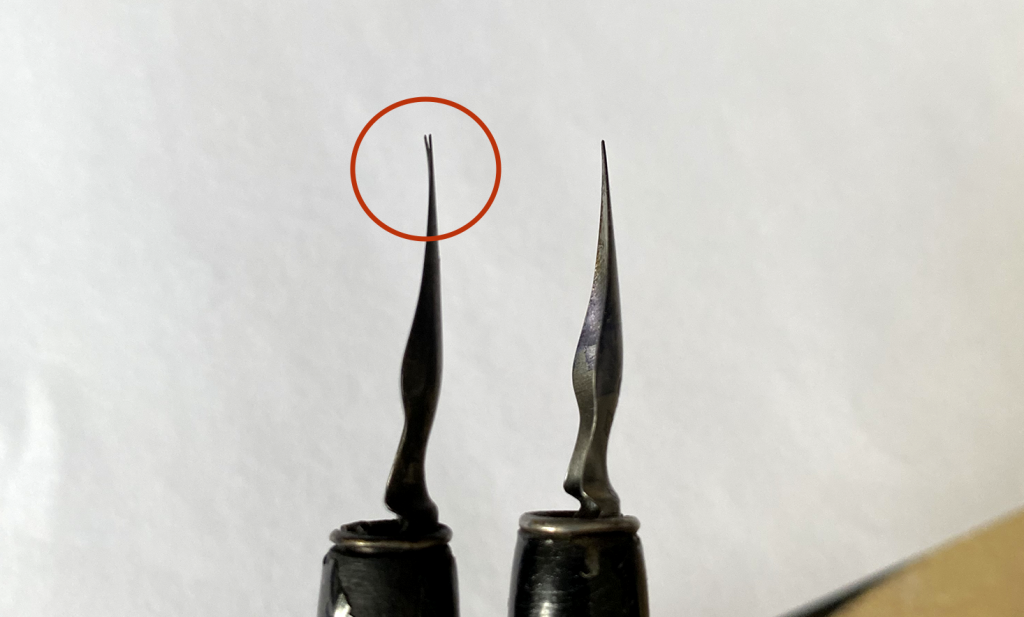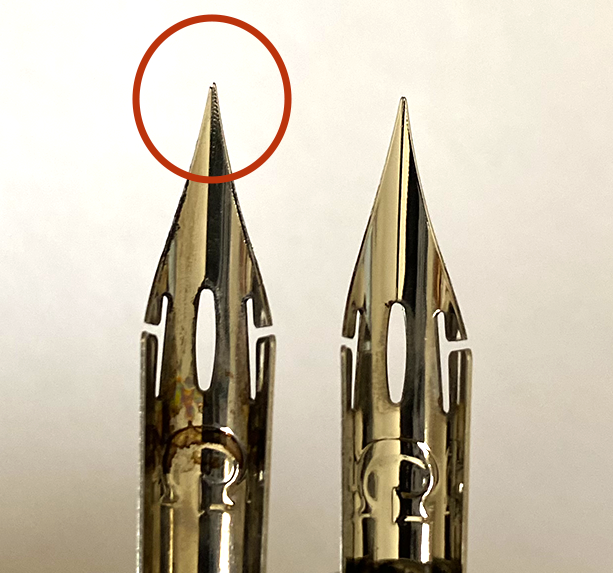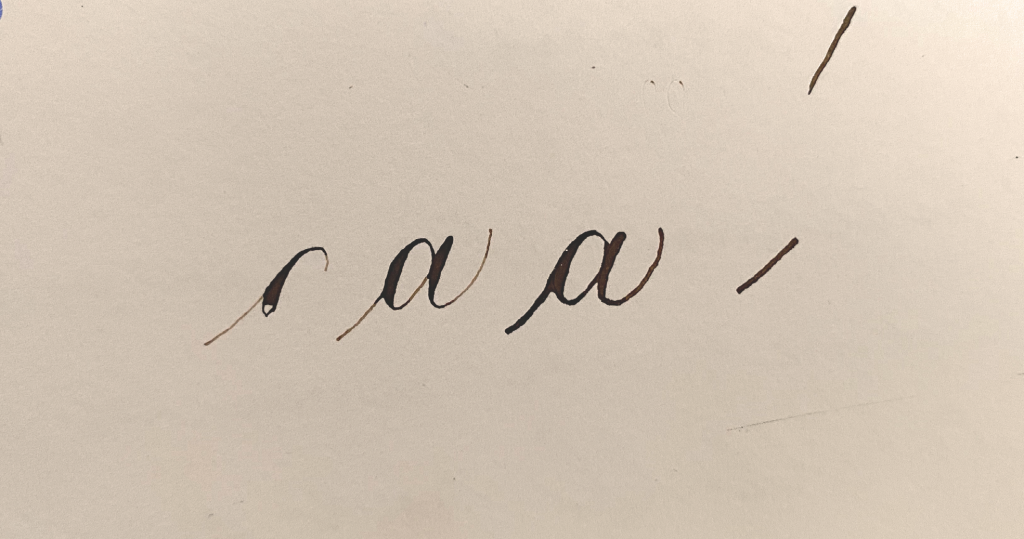
Cet été j’ai repris doucement la calligraphie à la plume pointue et j’ai peiné puissance 10. Mes traits étaient vraiment horribles et la plume accrochait considérablement le papier. Pensant que j’étais rouillée après de longs mois d’arrêt, j’ai persisté, en vain. J’ai incriminé le papier, puis l’encre. J’ai nettoyé 3 fois la plume, tourné ma feuille dans tous les sens, modifié l’inclinaison du porte-plume… Au passage je me suis un peu énervée aussi… Bref ! Jusqu’au moment où je me suis dit : « Essayons avec une plume neuve ! ». Et là, bien sûr, miracle !
Les plumes s’usent et certaines sont même très fragiles. Surtout si comme moi vous avez la main un peu lourde. Même avec une plume robuste comme la Nikko G, au fil des utilisations, ça se gâte.
Comment reconnaître qu’une plume est définitivement usée ?
Les signes d’usure sont différents pour les plumes pointues et les plumes biseautées. D’ailleurs, ces dernières s’usent nettement moins vite. La plume pointue est ultra fine, donc plus fragile, logiquement. Il m’est même arrivé d’en casser (et oui, en faisant de la gestuelle !).
Plume pointue usée : les signes
• La plume accroche le papier, alors que ce n’est pas le cas habituellement.
• Les déliés (parties fines de la lettre), sont plus gras que d’habitude.
• L’encre s’écoule mal : elle ne s’écoule pas sur les ascendantes et/ou fait des pâtés sur les descendantes.
La finesse du trait avec une plume usée, à droite
Que faire ? Généralement, tout ceci vient du fait que les 2 lames ne sont plus alignées et/ou que la pointe de la plume s’est légèrement courbée au fil des utilisations.
Exemple de lames abîmées qui ne sont plus alignées
Très difficile à voir à l’oeil nu, la pointe de gauche est très légèrement cassée
Il n’y a rien à faire, malheureusement, il faut passer sur une plume neuve.
Plume biseautée usée : les signes
• La plume manque de précision dans les traits d’attaque par exemple
• L’encre s’écoule mal, et/ou
• La plume est rouillée
Que faire ?
Plume rouillée : rien à faire, si ce n’est la nettoyer avec un produit un peu abrasif pour ôter la rouille (dentifrice, pierre d’argent, crème à récurer…). J’ai essayé les produits anti-rouille, sans succès. Si quelqu’un a déjà rattrapé une plume rouillée, qu’il/elle lève le doigt dans les commentaires !
Manque de précision : on peut, avec beaucoup de précautions, poncer une plume un peu émoussée. Pour cela, il faut utiliser une pierre d’Arkansas. C’est une pierre abrasive que l’on utilise notamment pour les gouges de gravure. Pour bien affûter la plume, il faut que toute la partie plate de la lame soit en contact perpendiculaire avec la pierre, et faire un léger mouvement de va-et-vient. Vous pouvez tester régulièrement la plume afin de ne pas trop l’affûter. Je précise ceci car il m’est arrivée de transformer une plume Brause en scalpel, et quand j’écrivais, elle coupait le papier !
La bonne inclinaison pour poncer, afin que la plume ne se transforme pas en cutter
Il faut juste se rappeler que c’est l’angle que l’on veut corriger, et non pas le fil des lames.
L’encre s’écoule mal : c’est peut-être juste un problème d’encrassage. Avec un produit nettoyant un peu abrasif et une brosse à dent, on arrive habituellement à restaurer une plume encrassée.
Conclusion
Si votre séance de calligraphie se déroule mal alors que vous utilisez le même papier et la même encre que d’habitude, vous avez peut-être juste besoin de changer de plume. N’oubliez pas de nettoyer votre plume neuve avant utilisation, afin de retirer le film de protection qu’elles ont en sortie de production. Pour cela, un petit nettoyage à l’eau tiède et au savon et c’est parti !